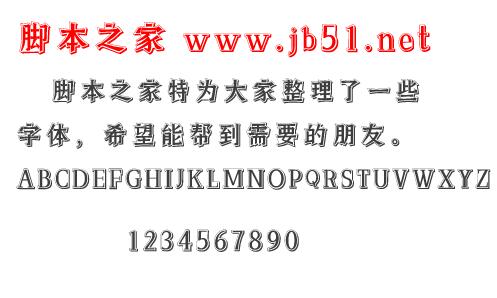
壹心風(fēng)潮宋是一款創(chuàng)意字體,字體在傳統(tǒng)宋體字的基礎(chǔ)上進(jìn)行了創(chuàng)新,字體中加入背景,使得立體感十足。并且保留了襯線的設(shè)計(jì),使字體的整體趣味性提高,給人帶來(lái)一種俏皮可愛(ài)的親切感。字體筆畫(huà)中尖角的襯線加強(qiáng)了字的個(gè)性和視覺(jué)沖擊力,使字體個(gè)性更加鮮明。
這款壹心風(fēng)潮宋還在字體中加入背景,使得字體筆畫(huà)之間相互聯(lián)系,立體感十足。彰顯了字體書(shū)寫(xiě)時(shí)的輕松自然,筆畫(huà)之間的相互呼應(yīng)。
壹心風(fēng)潮宋這款字體筆畫(huà)均衡分布、重心平穩(wěn),筆畫(huà)之間具有內(nèi)在的呼應(yīng)關(guān)系,起收有序、直而不僵、彎而不弱,字與字排列在一起時(shí)大小勻稱、行款整齊、流暢自然。